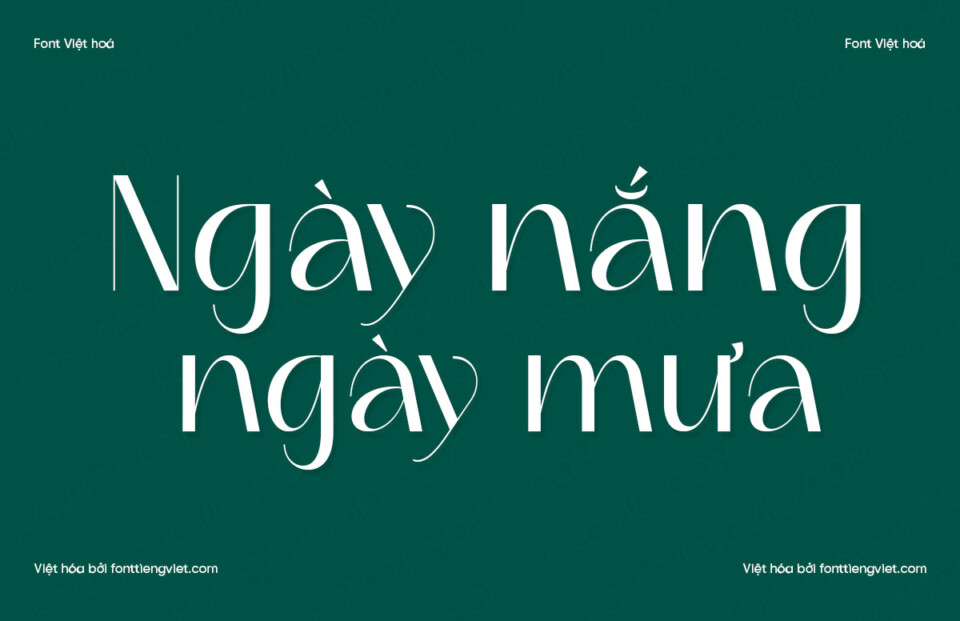
Font Việt hóa 1FTV VIP Lawraise
Tải Font Việt Hóa 1FTV VIP Lawraise – Đỉnh Cao Của Sự Sang Trọng
Bạn đang tìm kiếm một phông chữ (typography) toát lên vẻ đẹp thanh lịch, quý phái và đầy tính nghệ thuật? Font Việt hóa 1FTV VIP Lawraise chính là “mảnh ghép” hoàn hảo mà các nhà thiết kế đồ họa không nên bỏ qua. Nằm trong bộ sưu tập phông chữ cao cấp, Lawraise mang đến sự giao thoa tuyệt vời giữa nét đẹp cổ điển và hơi thở hiện đại.
Đặc Điểm Nổi Bật Của Font 1FTV VIP Lawraise
Được tinh chỉnh bởi đội ngũ thiết kế chuyên nghiệp, bộ font này sở hữu những ưu điểm vượt trội:
• Hỗ trợ tiếng Việt hoàn hảo: Các dấu câu và ký tự có dấu được kerning (căn chỉnh khoảng cách) và vẽ lại tỉ mỉ, đảm bảo văn bản hiển thị mượt mà, không bị lỗi font trên mọi phần mềm thiết kế như Photoshop, Illustrator hay Canva.
• Đường nét tinh tế: Sự tương phản rõ rệt giữa nét thanh và nét đậm tạo nên hiệu ứng thị giác mạnh mẽ, giúp dòng chữ trở nên sắc sảo và cuốn hút người xem ngay từ ánh nhìn đầu tiên.
• Phong cách Luxury: Thể hiện trọn vẹn sự đẳng cấp, rất phù hợp cho các dự án yêu cầu tính thẩm mỹ cao.
Ứng Dụng Đa Dạng Trong Thiết Kế Đồ Họa
Nhờ thiết kế sang trọng, 1FTV VIP Lawraise là sự lựa chọn hàng đầu cho nhiều ấn phẩm truyền thông:
• Nhận diện thương hiệu: Thiết kế Logo, Namecard, bao bì cho các ngành hàng thời trang cao cấp, mỹ phẩm, trang sức, spa và bất động sản.
• Ấn phẩm in ấn: Tuyệt đẹp khi sử dụng làm tiêu đề cho thiệp cưới, thư mời sự kiện, bìa tạp chí, catalogue hoặc poster nghệ thuật.
• Thiết kế Web & Social: Tạo điểm nhấn ấn tượng cho banner quảng cáo và các bài đăng trên mạng xã hội.